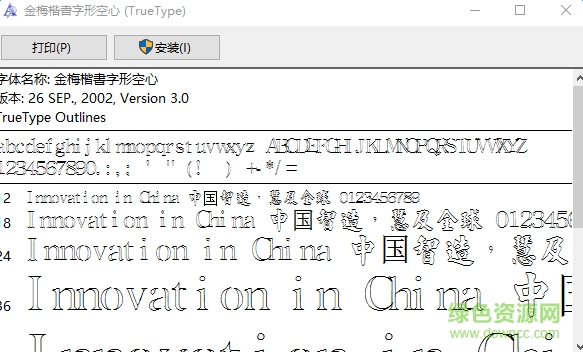
金梅楷書字形空心字體是金梅字庫中的一款空心字體,這款字體是很有個(gè)性的,寫出來的字也是很好看的,也是深受廣大朋友們的喜歡,小編已經(jīng)將這款字體打包好了,歡迎大家來綠色資源網(wǎng)下載。
金梅楷書字形空心字體是一款很有特色的電腦字體,字形工整美觀,而且實(shí)用性強(qiáng),可以用于很多方面,歡迎大家來綠色資源網(wǎng)下載。